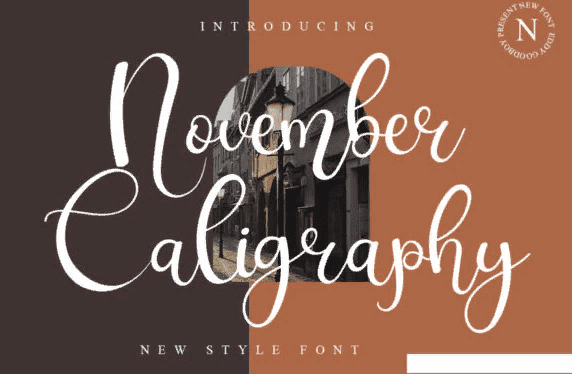
Название: November Caligraphy Font (2021)
November Caligraphy - это изысканный рукописный шрифт, мастерски разработанный, чтобы стать настоящим фаворитом.
Он сохраняет свое стильное каллиграфическое влияние, но при этом чувствует себя современным и свежим.
Название: November Caligraphy Font (2021)
November Caligraphy - это изысканный рукописный шрифт, мастерски разработанный, чтобы стать настоящим фаворитом.
Он сохраняет свое стильное каллиграфическое влияние, но при этом чувствует себя современным и свежим.